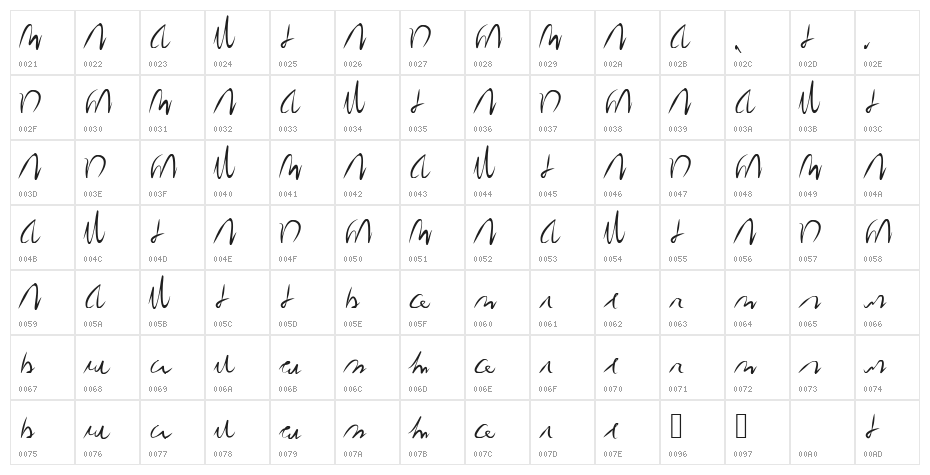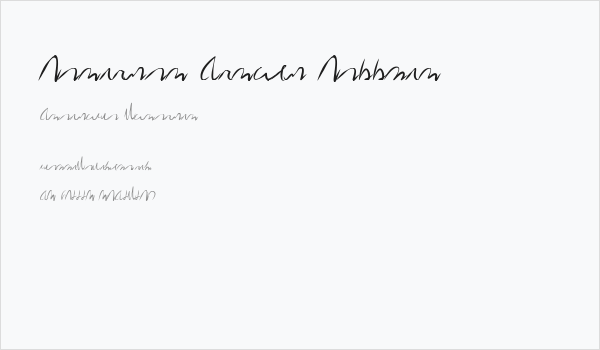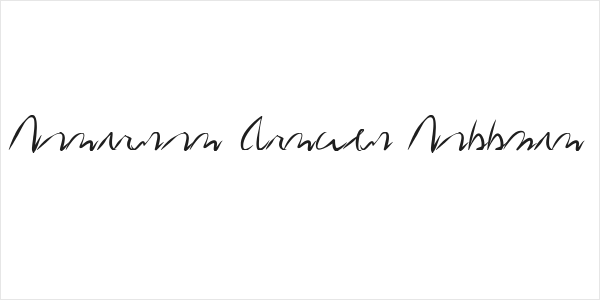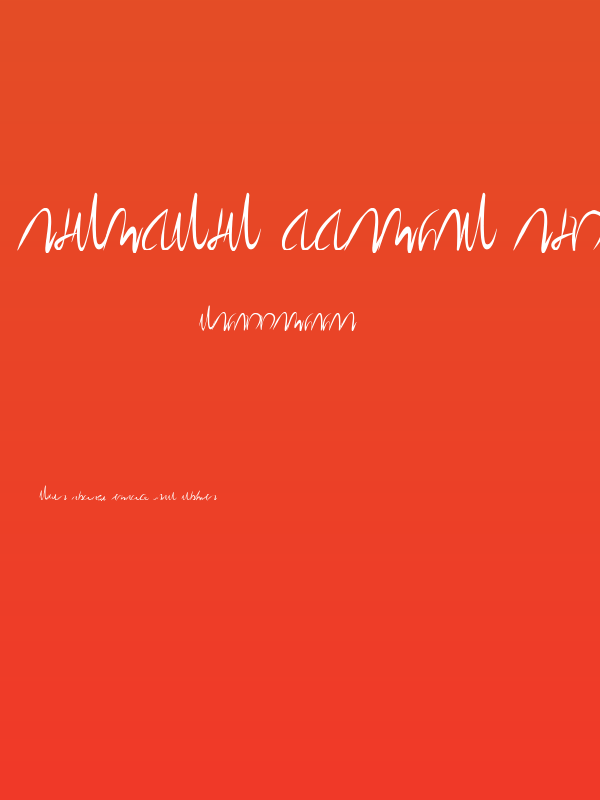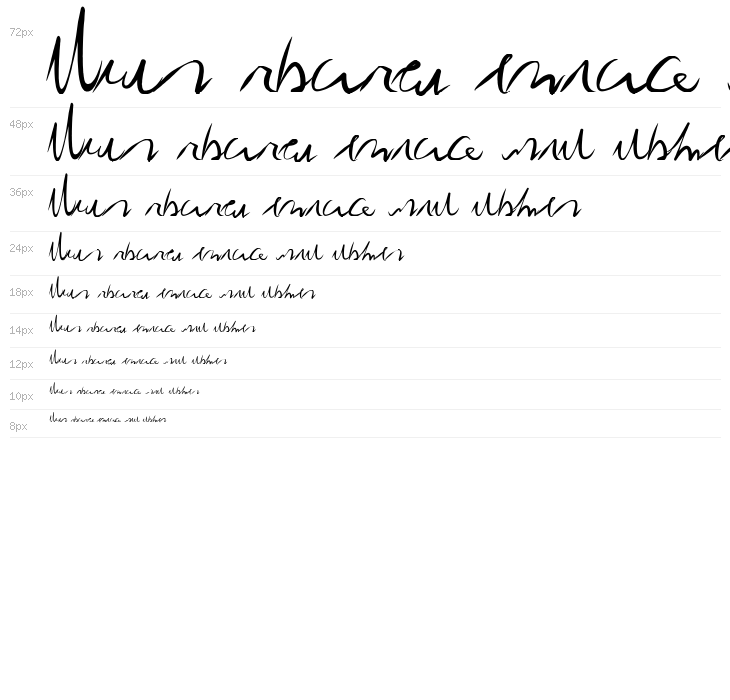
Redacted Script Regular Font
| Caso d'uso | Artistic designs, creative branding, abstract art. |
| Progetti proposti | Ideal for artistic designs, abstract art pieces, creative branding, and modern art installations. |